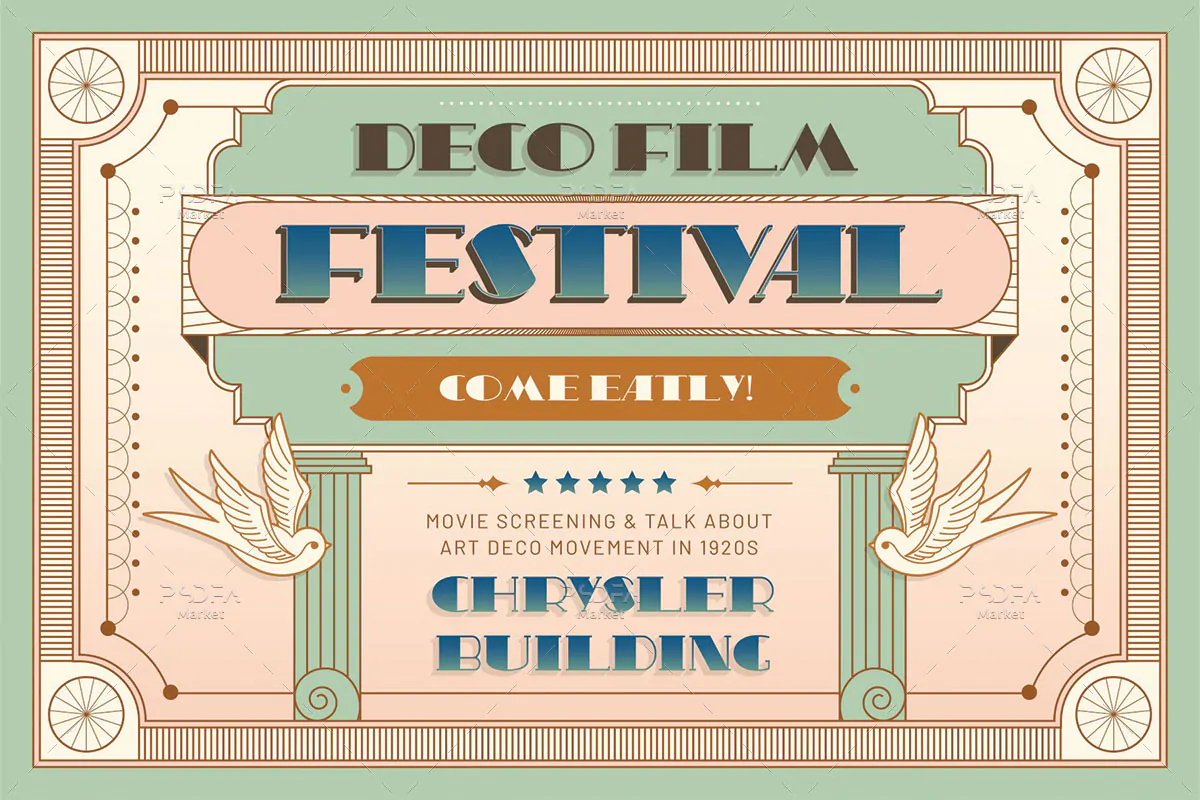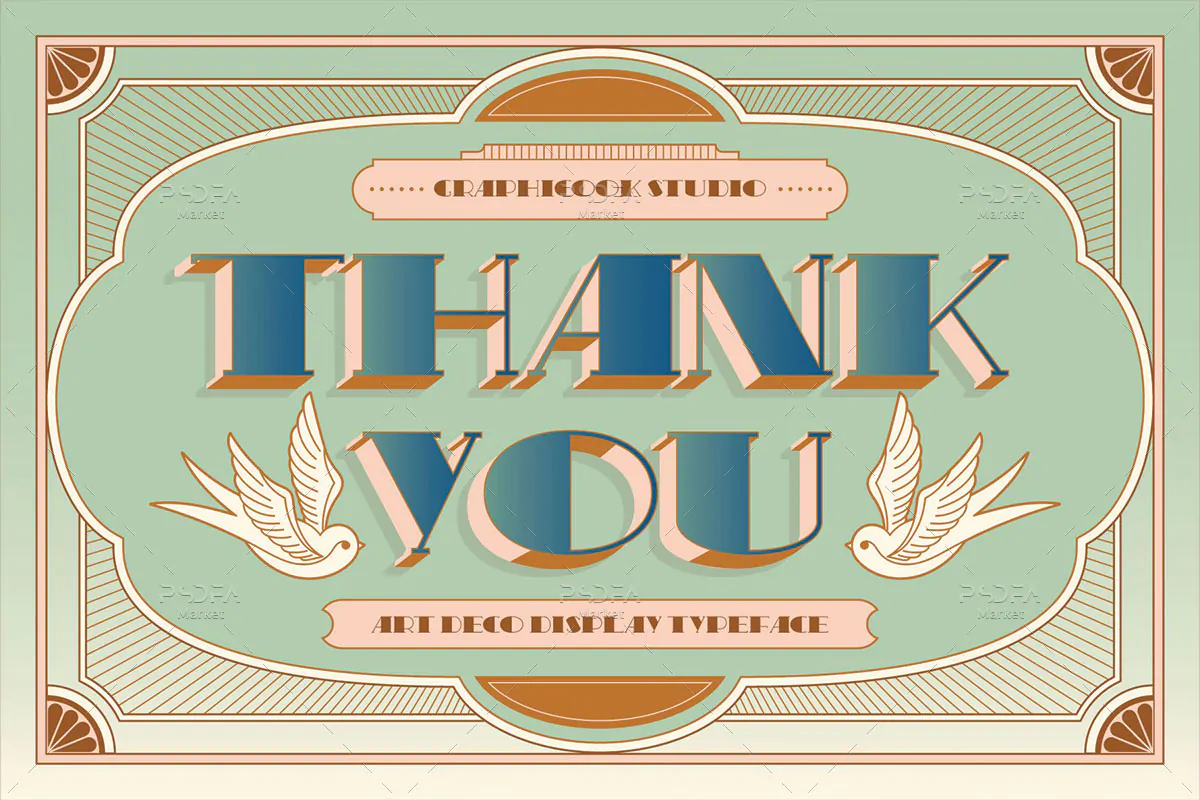
فونت دکوراتیو و تزئینی کلاسیک Gc Nerts Deco
فونت دکوراتیو و تزئینی کلاسیک
فونت دکوراتیو و تزئینی کلاسیک Gc Nerts Deco یک قلم نمایشی انگلیسی به سبک فونتهای رترو است که مناسب جهت استفاده در طرح و پروژههای گرافیکی مختلف میباشند. فونت Gc Nerts Deco با وزن معمولی طراحی شده است که میتوانید از آن در طراحی پوستر، بسته بندی محصولات، چاپ انواع لیبل و برچسب نوشیدنی، ظروف یکبار مصرف و … استفاده کنید.